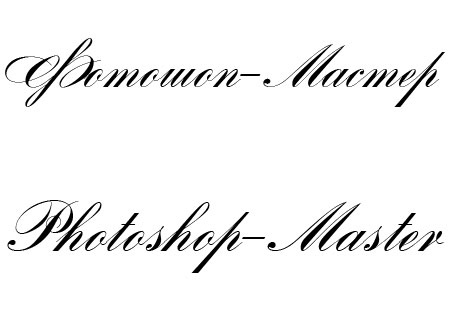
Красивые заглавные буквы!!!
Спасибо очень красивый шрифт
Изумительный шрифт!
Мне очень понравилось!
клевый шрифт...спасибо
Спасибо!!!Изящный щрифт.
Красиво и оригинально.!!!!!!
красиво! спасибо!
Чудненько!